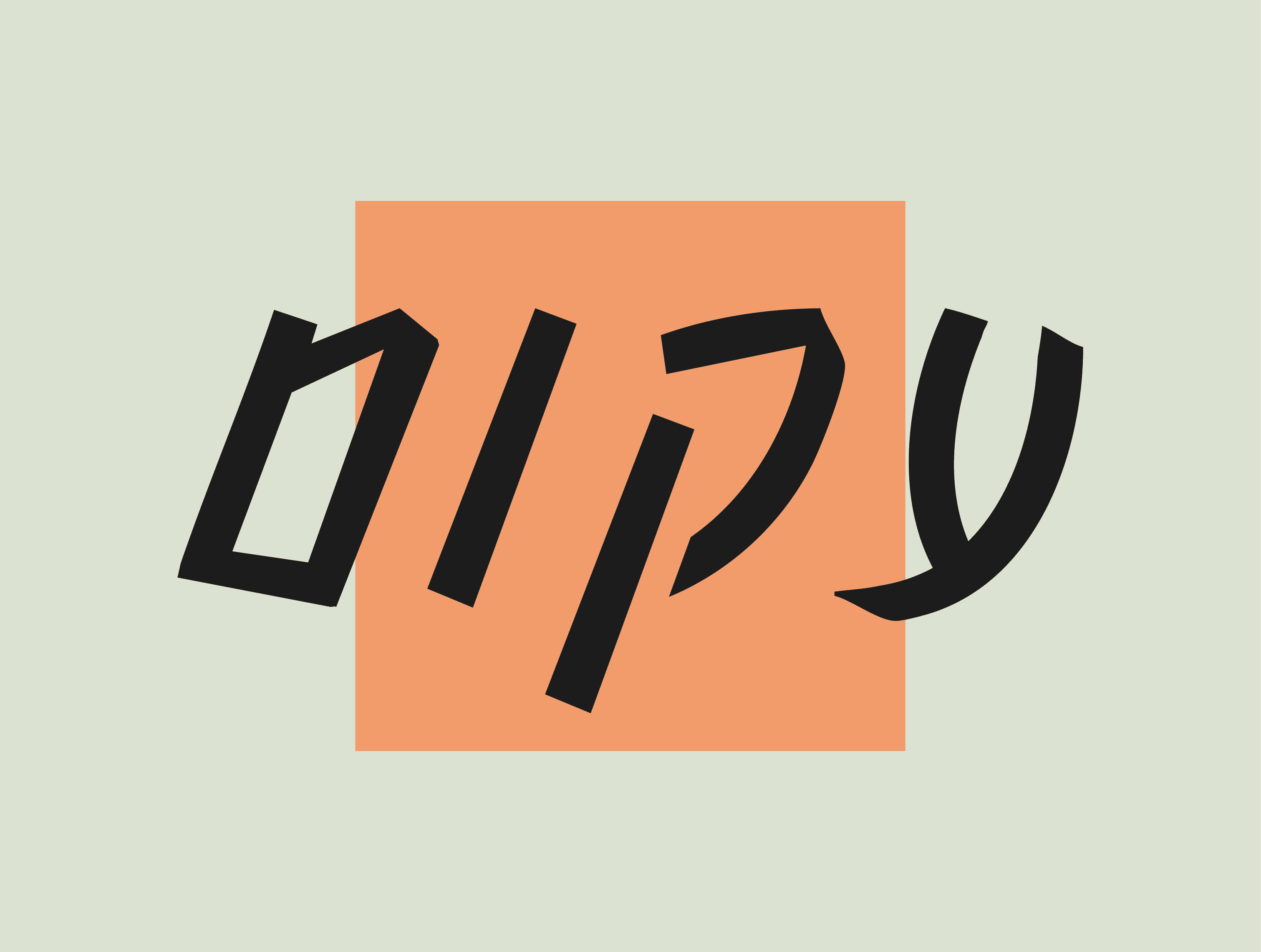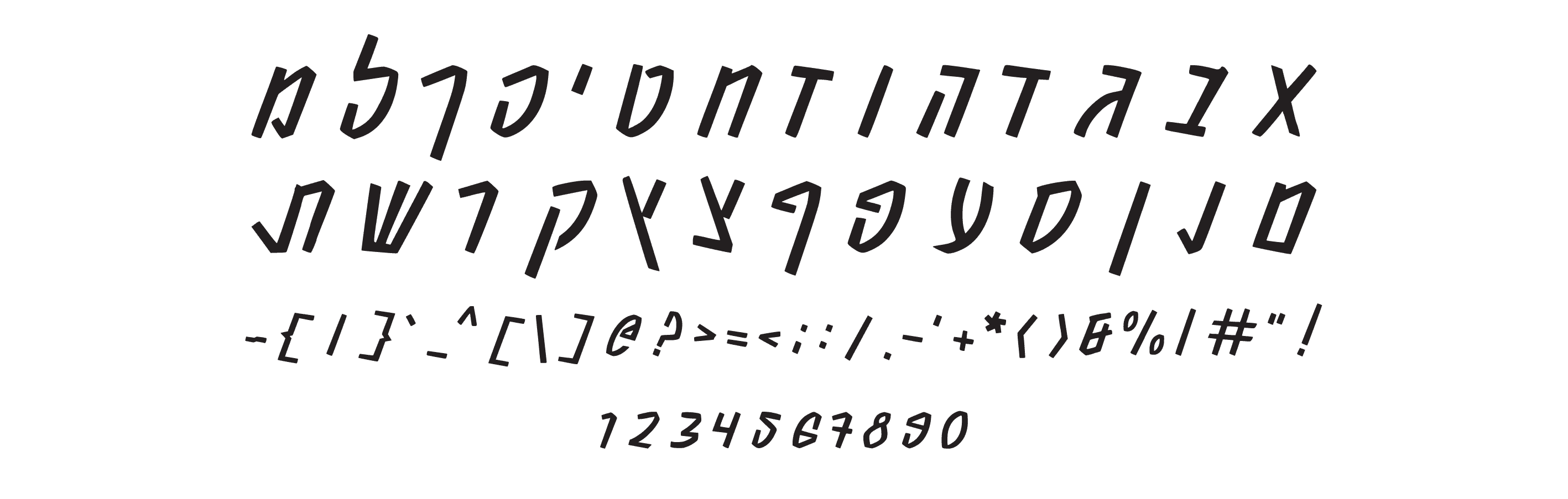
פונט עקום
פונט עברי זוויתי ומוטה, מושלם לפוסטרים, לוגואים ועיצובים יצירתיים ונועזים.
עקום — הפונט שלא הולך ישר
לפעמים דווקא החוסר-שלמות הוא זה שמושך את העין.
עקום הוא פונט זוויתי, בועט ובעל נוכחות — עם אותיות שנוטות בזוויות חדות ויוצרות תחושת תנועה ושובבות.
זהו פונט שלא מפחד להיות שונה, והוא מכניס כל עיצוב למצב רוח אחר: צעיר, נועז, קצת עקום — בכוונה.
מושלם לכל עיצוב שמחפש לצאת מהשגרה, להפתיע, ולהעביר מסר בגובה העיניים אך עם סטייה מכוונת מהמסלול.
איפה הוא מרגיש בבית?
🔶 פוסטרים בועטים ונועזים
🔶 לוגואים חתרניים
🔶 עיצובים למוזיקה, אירועים או מותגים צעירים
🔶 כל עיצוב שלא רוצה להיות "מרובע"
למי הוא מתאים?
למעצבים שמחפשים פונט שמביא איתו תעוזה, תנועה וחיוך קטן בזווית העין.